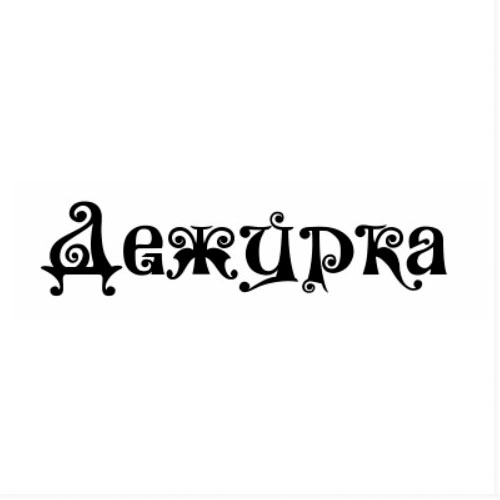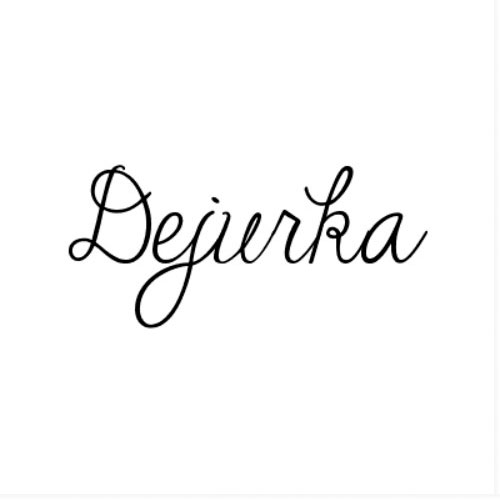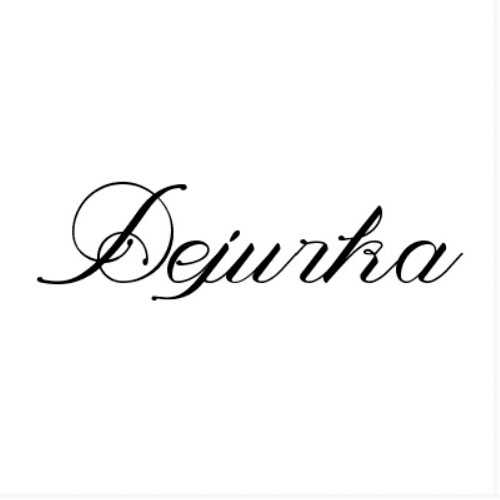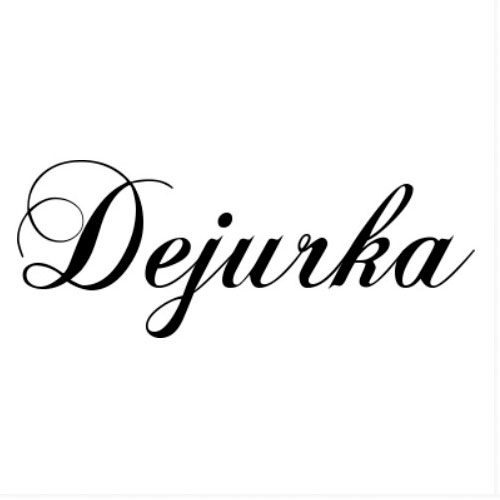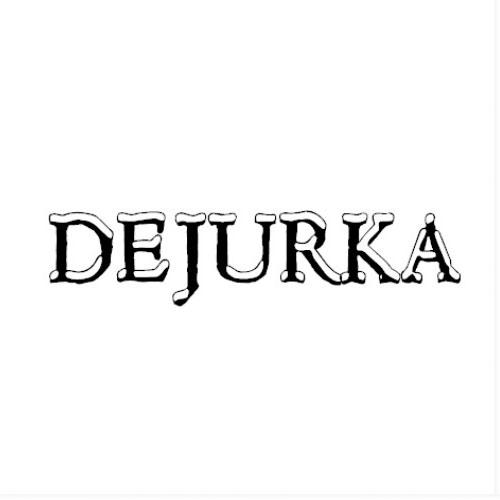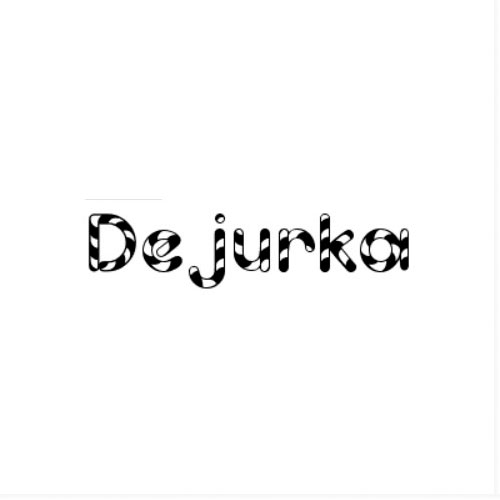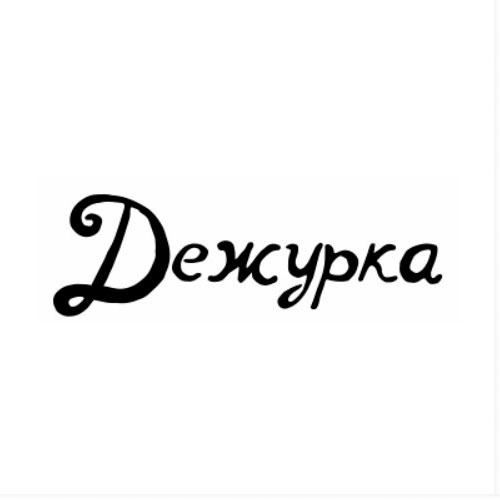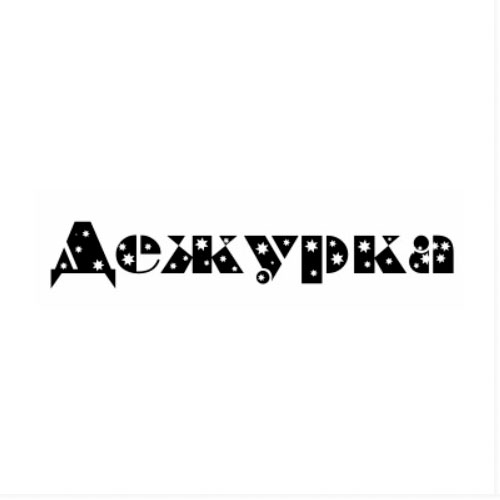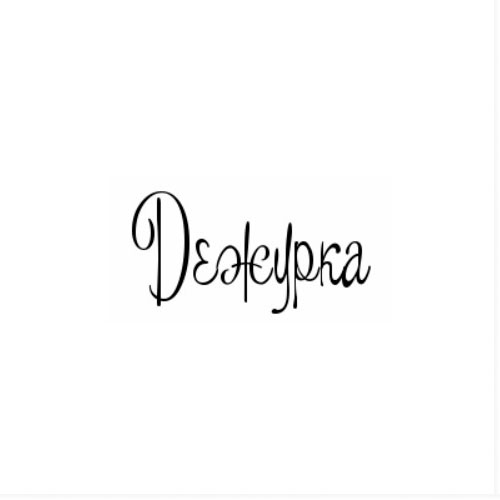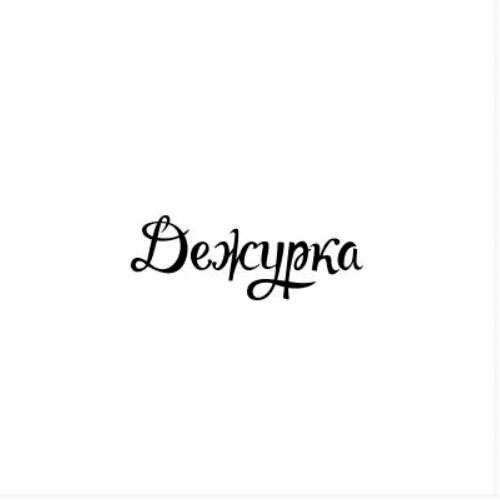
Бесплатные праздничные шрифты
Эта подборка, возможно, сэкономит ваше время и силы, которое вы собирались потратить на поиски новогодних шрифтов в интернете. Мы собрали как латинские так и кириллические шрифты, которые подходят для оформления праздничного дизайна.
Кириллица
Wonderland
notperfect regular
a_BraggaStars
Campanella
RupsterScriptFree
Pudelinka
Majestic X
Aquarelle
Латиница
Things We Said
Janda Cheerful Script
Magnolia
Chopin Script
Hultog Snowdrift
Contribute
Candy Cane